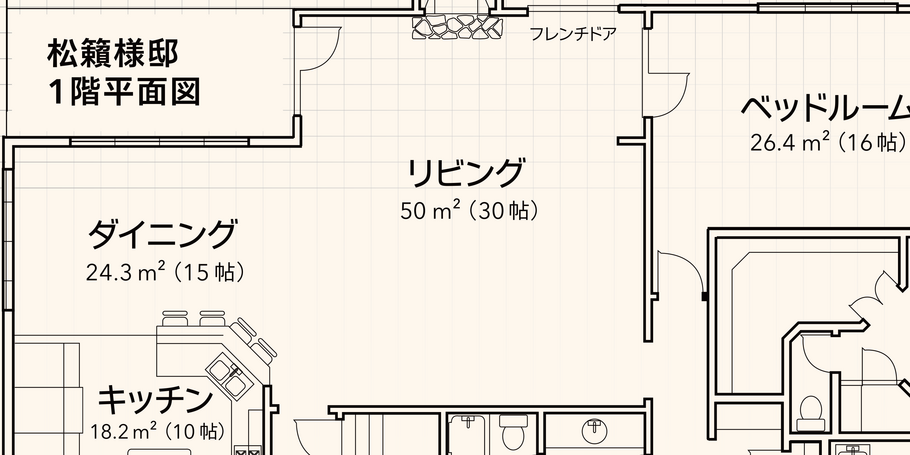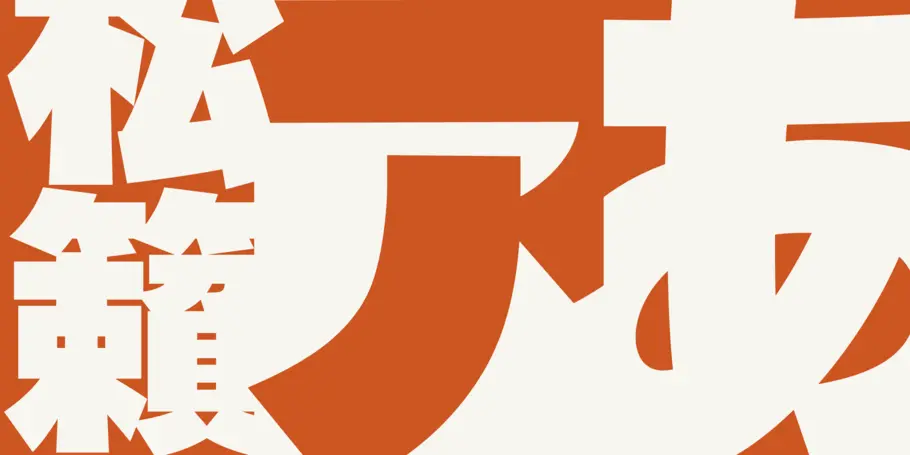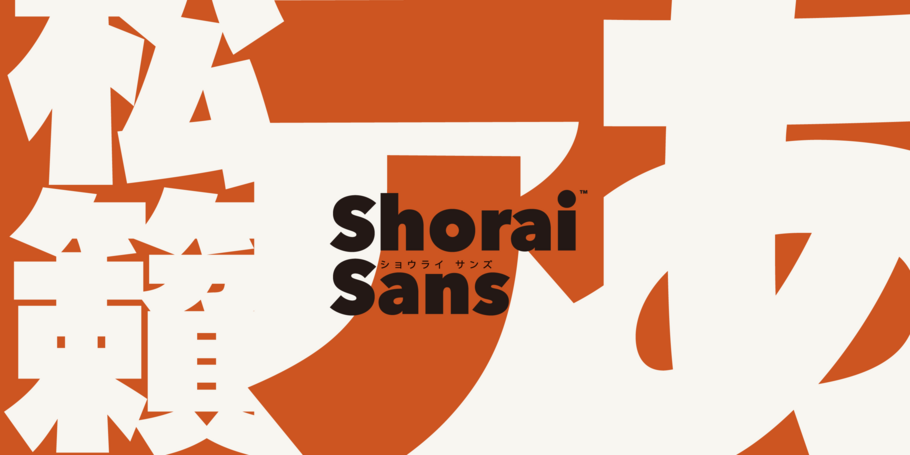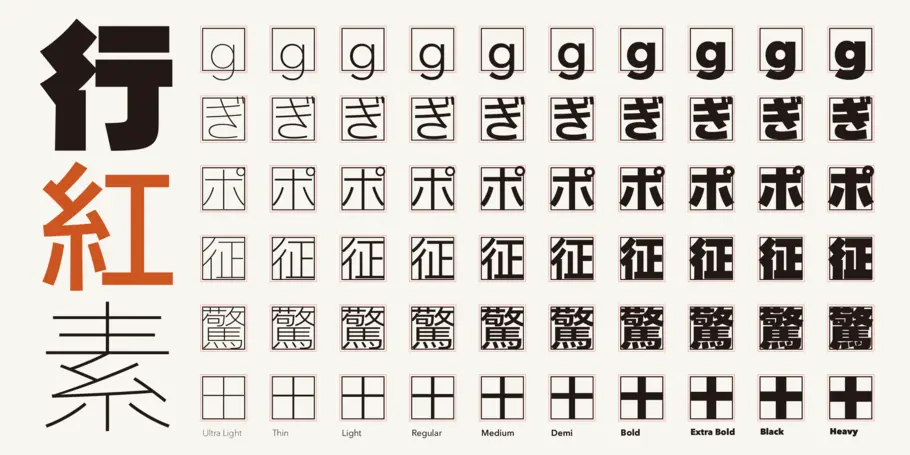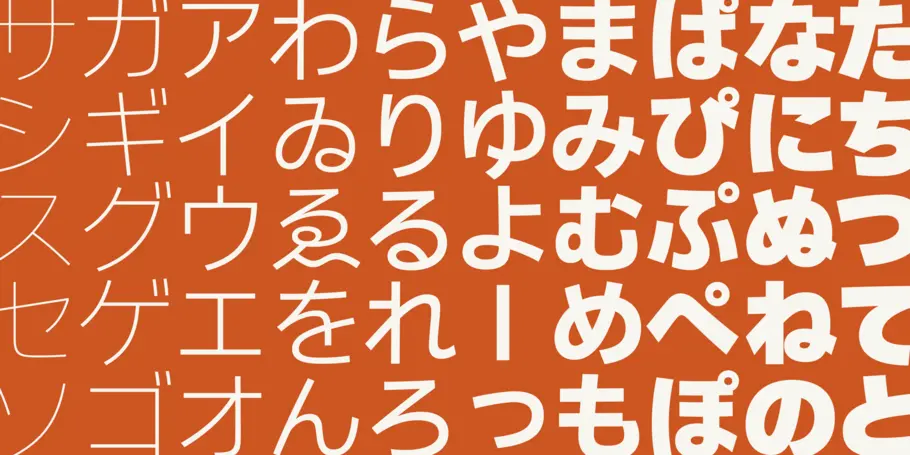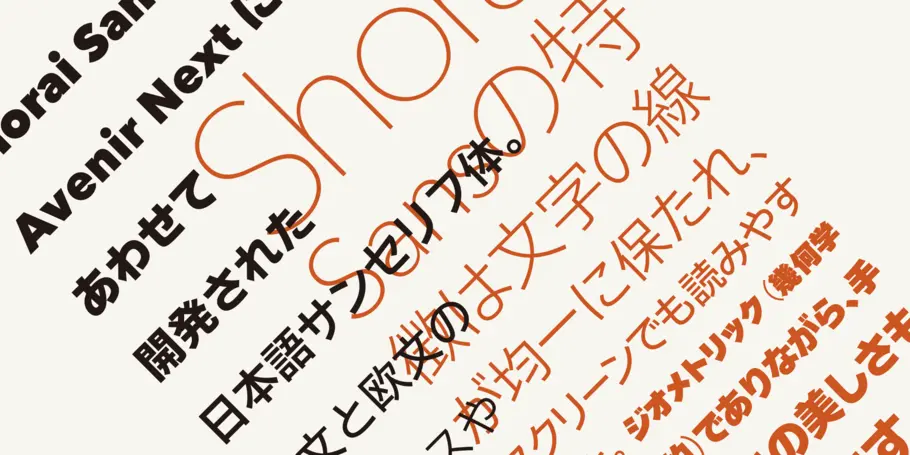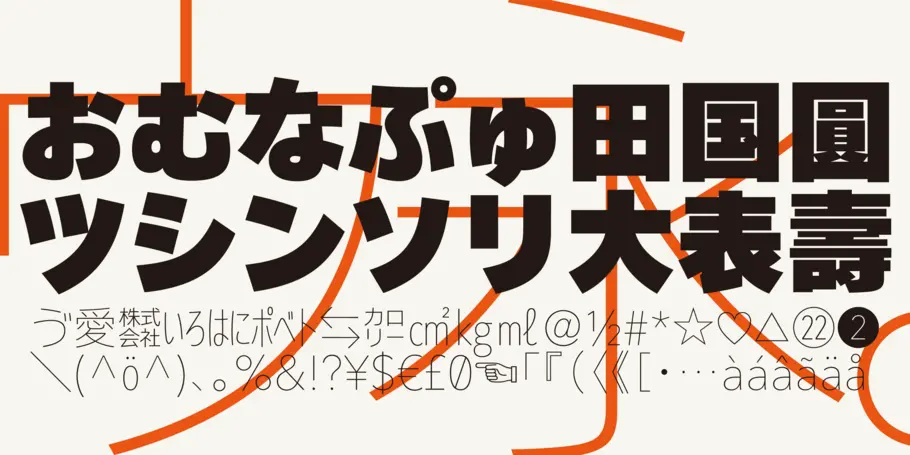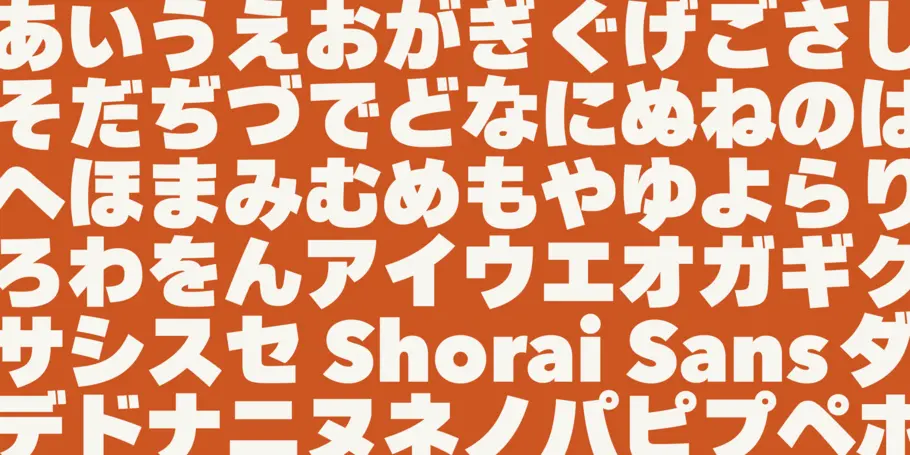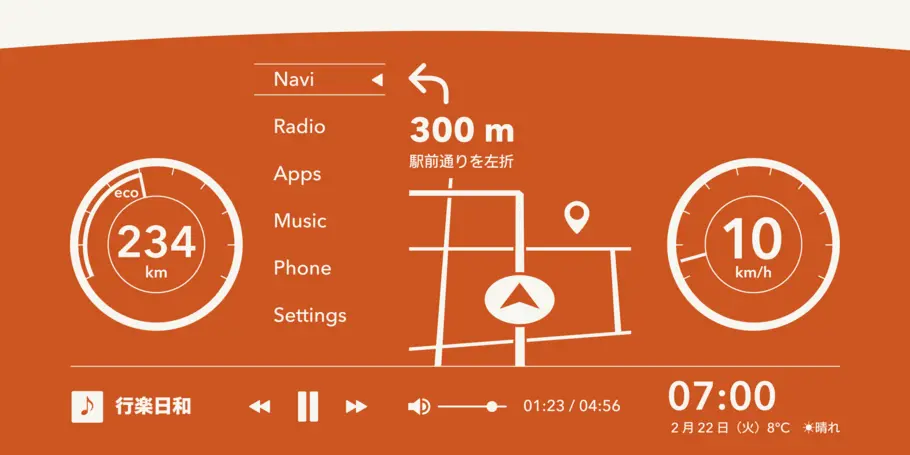
Shorai® Sans
La voix de l’essentiel.
Shorai® Sans évoque l’équilibre entre les subtils coups de pinceau traditionnels dessinés à la main et les contours géométriques nets. Basée sur les principes de la conception universelle, avec ses formes de lettres simplifiées et sa vaste gamme de graisses, Shorai® Sans ouvre de nouveaux horizons dans la typographie japonaise.
Shorai® Sans évoque l’équilibre entre les subtils coups de pinceau traditionnels dessinés à la main et les contours géométriques nets. Basée sur les principes de la conception universelle, avec ses formes de lettres simplifiées et sa vaste gamme de graisses, cette sans-serif ouvre à nouveau cet horizon de la typographie japonaise.
Shorai® Sans a été conçu comme un complément à Avenir® Next, pour s’intégrer harmonieusement dans les designs modernes, tout en préservant l’essence de l’écriture japonaise.
Basée sur les principes de la conception universelle, Shorai va au-delà des sans serifs japonais existants pour offrir un large éventail de graisses et de caractères avec lesquelles les designers peuvent expérimenter. Shorai® Sans ouvre de nouveaux horizons dans la typographie japonaise.
Akira Kobayashi, directeur typographe, possède trois décennies d’expérience et une connaissance approfondie de la typographie japonaise, ainsi qu’une compréhension approfondie de la calligraphie. Après quatre ans d’études à l’université d’art de Musashino à Tokyo, Akira Kobayashi a commencé par travailler dans l’entreprise de composition photo Sha-Ken Co. où il s’est consacré au processus long et compliqué du design de caractères japonais.
Ryota Doi est designer typographique chez Monotype. Il s’est intéressé à cette discipline lorsqu’il a commencé ses études au Japon. Après avoir obtenu un Bachelor of Arts en design à l’université des arts de Tokyo, il s’est inscrit pour un Master en Typeface Design à la célèbre Université de Reading, où il a étudié les différences entre les caractères japonais et latins.
M. Yukihiro Nakamura est un typographe légendaire au Japon. Dans le domaine de la création de caractères japonais, un virage sismique a été pris dans les années 1970. M. Nakamura est responsable de ce changement que l’on peut presque qualifier de paradigmatique.